Top 5 Font chữ viết tay thiệp cưới, font Việt hóa thiệp cưới
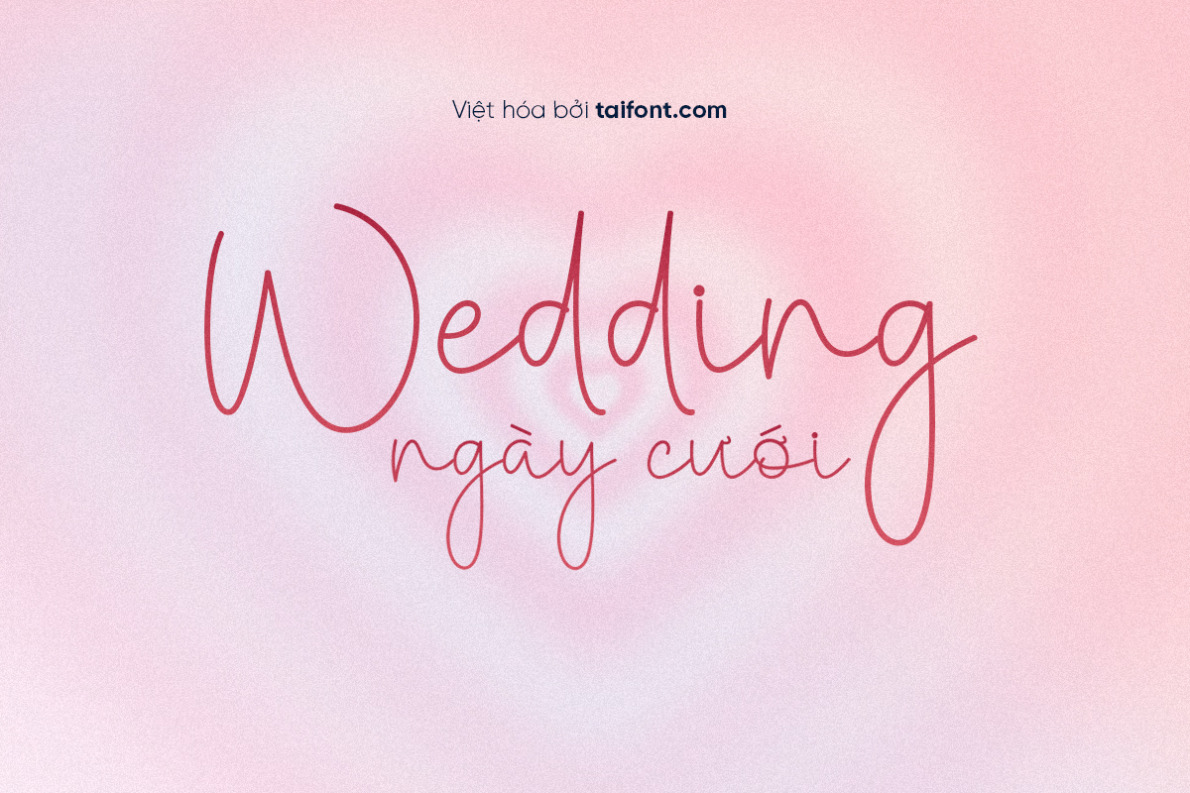
Top 5 Font chữ viết tay thiệp cưới, font Việt hóa thiệp cưới là những font chữ không thể thiếu để thiết kế thiệp cưới. Đây là những font chữ thú vị có thể sử dụng.
Top 1: Font Việt hóa TF Benjamin Kingdom
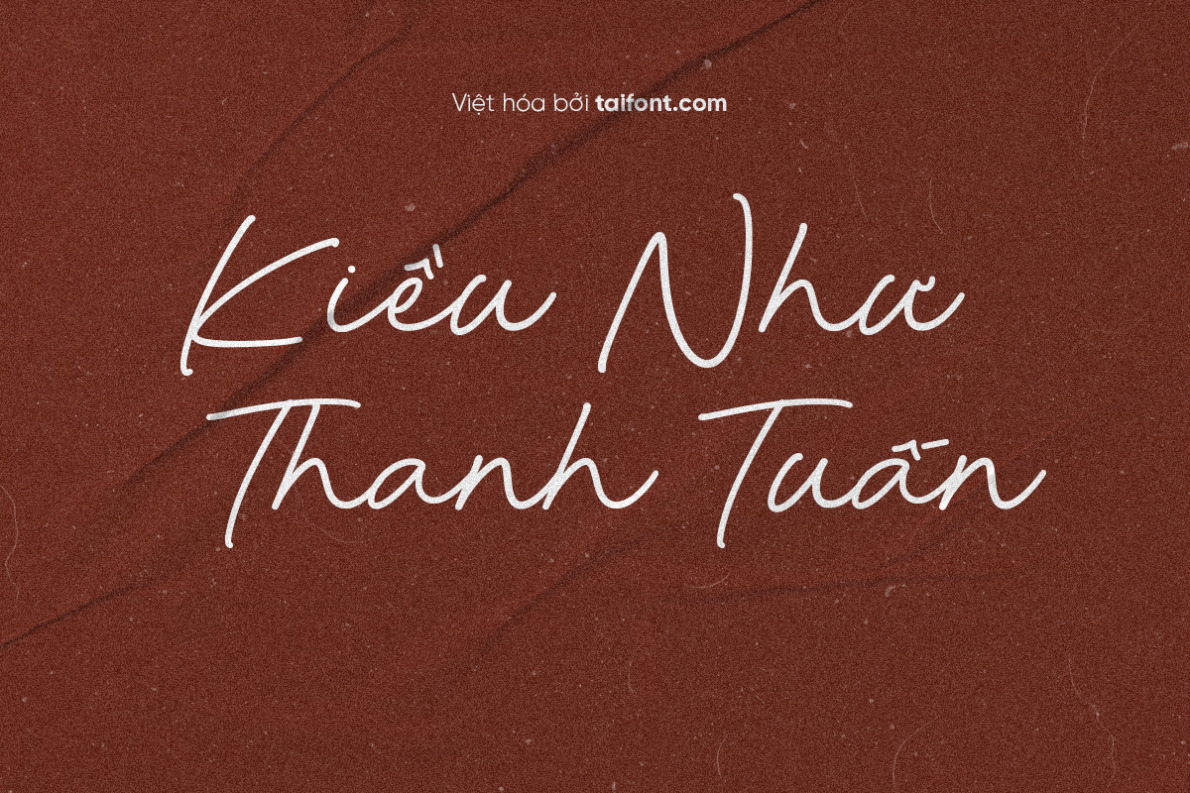
Font Việt hóa TF Benjamin Kingdom là một phông chữ viết tay Monoline. Phông chữ này là một phông chữ viết tay Monoline thời trang với cảm giác thanh lịch và hiện đại.
Các nét chữ mượt mà, uyển chuyển và hình dạng chữ cân bằng làm cho nó hoàn hảo cho logo, thương hiệu
Top 2: Font Việt hóa TF Carolina
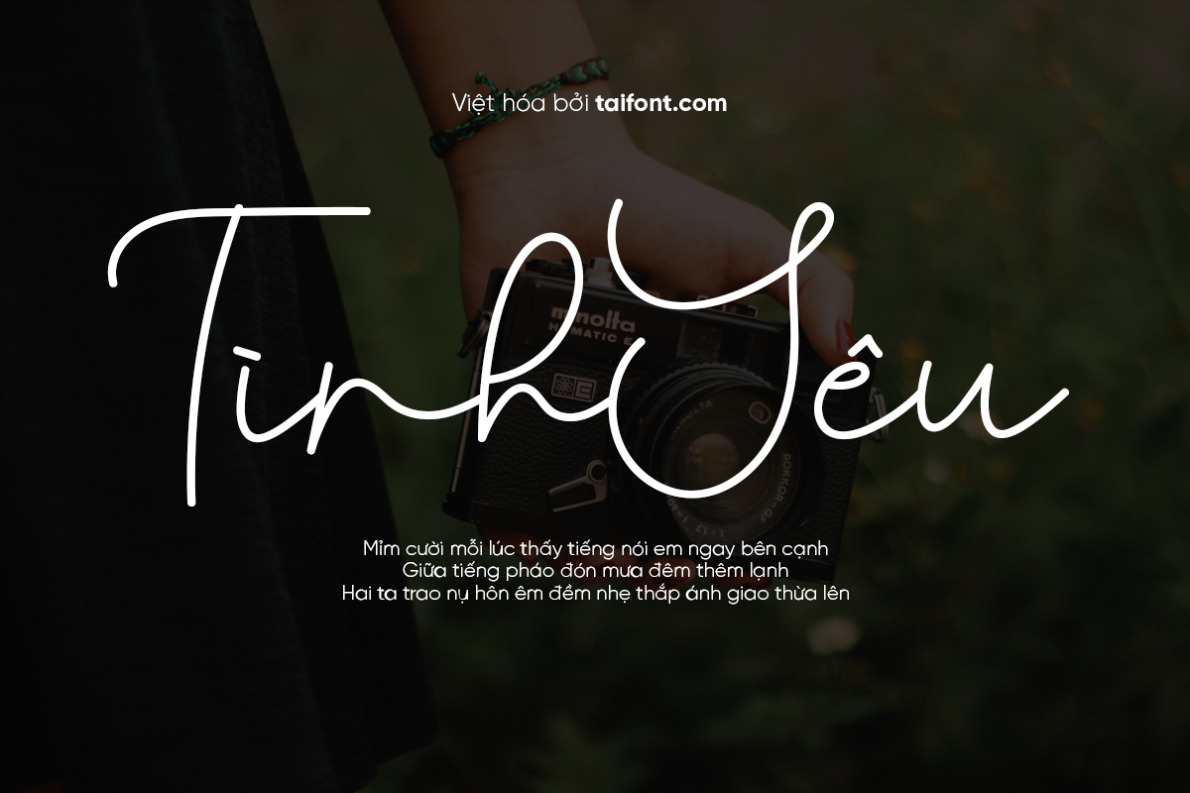
Font Việt hóa TF Carolina là một phông chữ script thời trang và vô cùng thanh lịch.
Nó trông tuyệt đẹp trên thiệp mời đám cưới, thiệp cảm ơn, trích dẫn, thiệp chúc mừng, logo, danh thiếp và mọi thiết kế khác cần nét viết tay.
Top 3: Font Việt hóa TF Something
Font Việt hóa TF Something là một phông chữ viết tay ngọt ngào và thân thiện. Phong cách tự nhiên và độc đáo của nó làm cho nó cực kỳ phù hợp với một nhóm lớn các thiết kế
Top 4: Font Việt hóa TF Permatha Signature
Font Việt hóa TF Permatha Signature là một font chữ ký, phù hợp với thiết kế thiệp mời, thiệp cưới.
Top 5: Font Việt hóa TF Autthentic
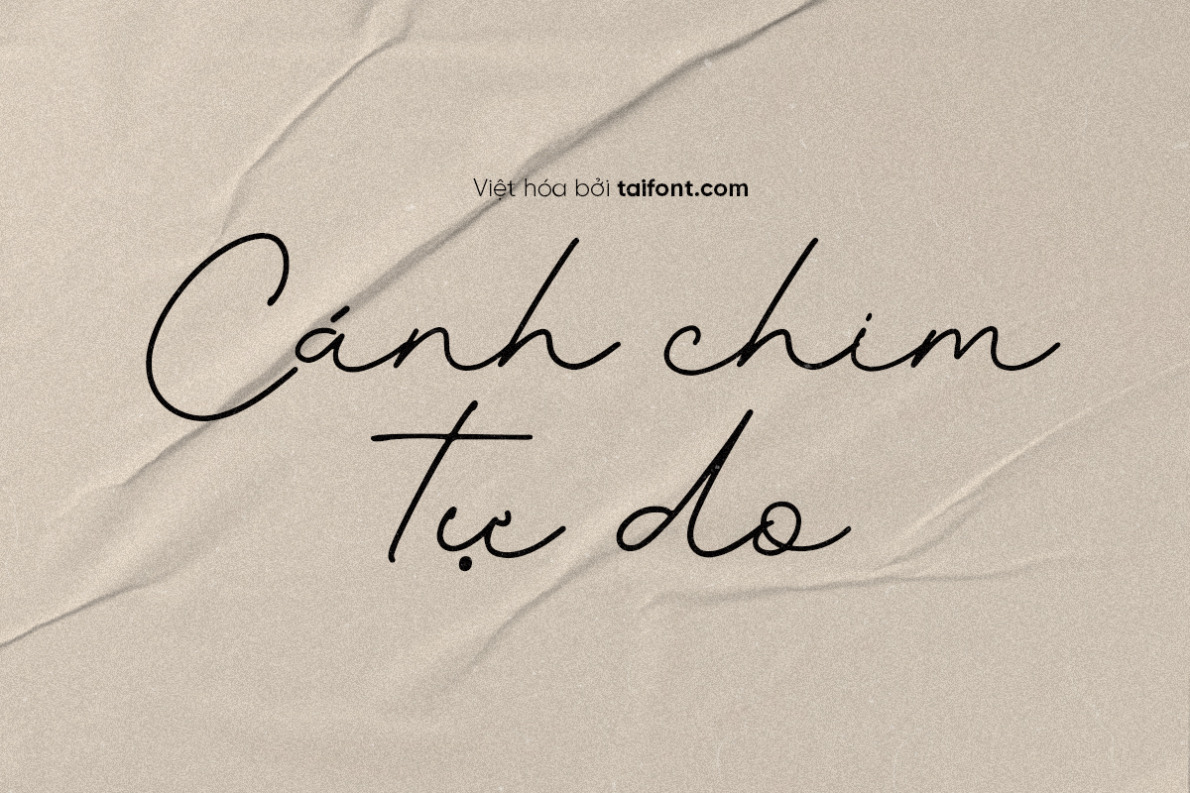
Font Việt hóa TF Autthentic là font chữ viết tay toát lên vẻ thanh lịch và hiện đại.
Với nét chữ mượt mà và vẻ ngoài tự nhiên, phông chữ này hoàn hảo cho nhiều nhu cầu thiết kế như logo, thiệp đám cưới, thiệp chúc mừng, xây dựng thương hiệu và nội dung truyền thông xã hội.